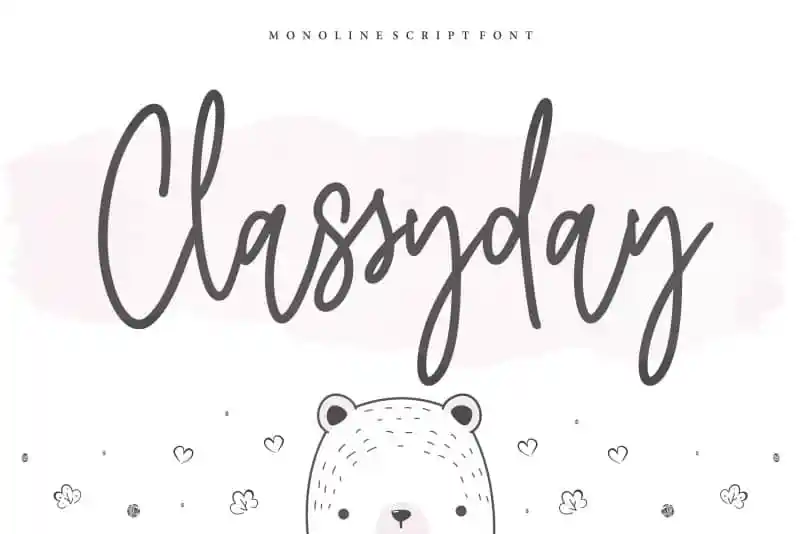
Classyday Monoline Script Font
A fonte ‘Classyday Monoline Script Font’ do designer balpirick é uma excelente escolha para qualquer projeto que precise de um efeito elegante e sofisticado. Perfeita tanto para uso nas embalagens dos produtos quanto na criação de marcas, esta fonte proporciona um estilo único e moderno capaz de destacar qualquer design. Seja em revistas, mídias sociais ou até mesmo para anúncios de casamento, ‘Classyday Monoline Script Font’ traz elegância e profissionalismo ao seu projeto, facilitando a expressão das ideias acima do fundo. Ideal tanto para aplicar sobre textos quanto em backgrounds, é uma escolha inteligente para quem busca uma fonte que transmita sofisticação e qualidade. Com certeza será um recurso valioso no seu portfólio de criações gráficas.